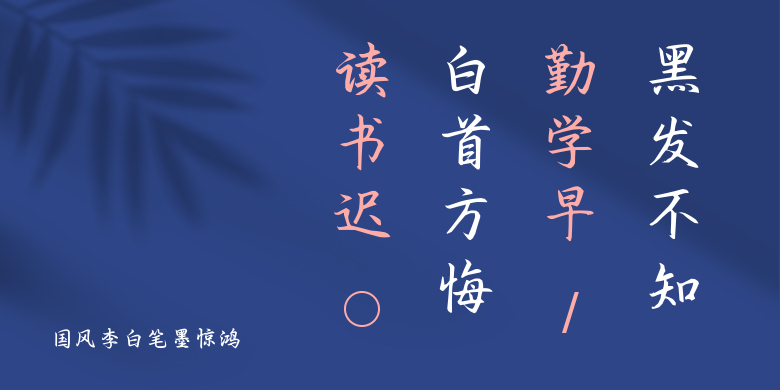
国风李白笔墨惊鸿
国风李白笔墨惊鸿,这款字体结构工整、笔画清晰,兼顾美观与易读性,适用于标题、正文、海报、包装、LOGO 等多种场景。字形优雅稳定,风格百搭耐看,适配日常排版与创意设计,让文字呈现更舒适、更具质感。国风李白笔墨惊鸿一笔一画,皆是细节,以均衡的比例、流畅的线条打造舒适视觉体验,字形端正大气,风格简约现代。无论是商业设计、品牌宣传还是日常排版,都能轻松驾驭,让文字更有格调与力量。国风李白笔墨惊鸿字体下载。